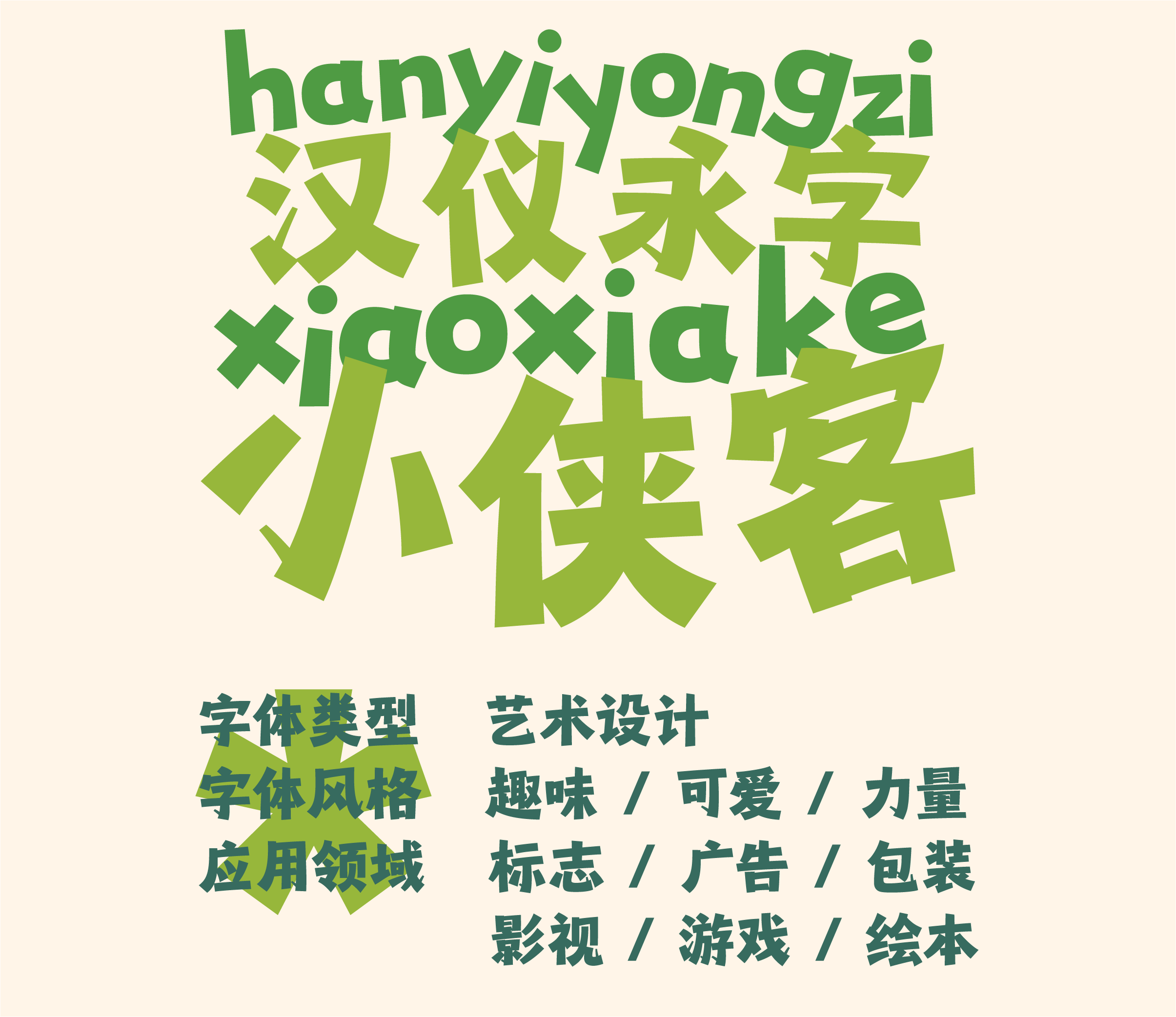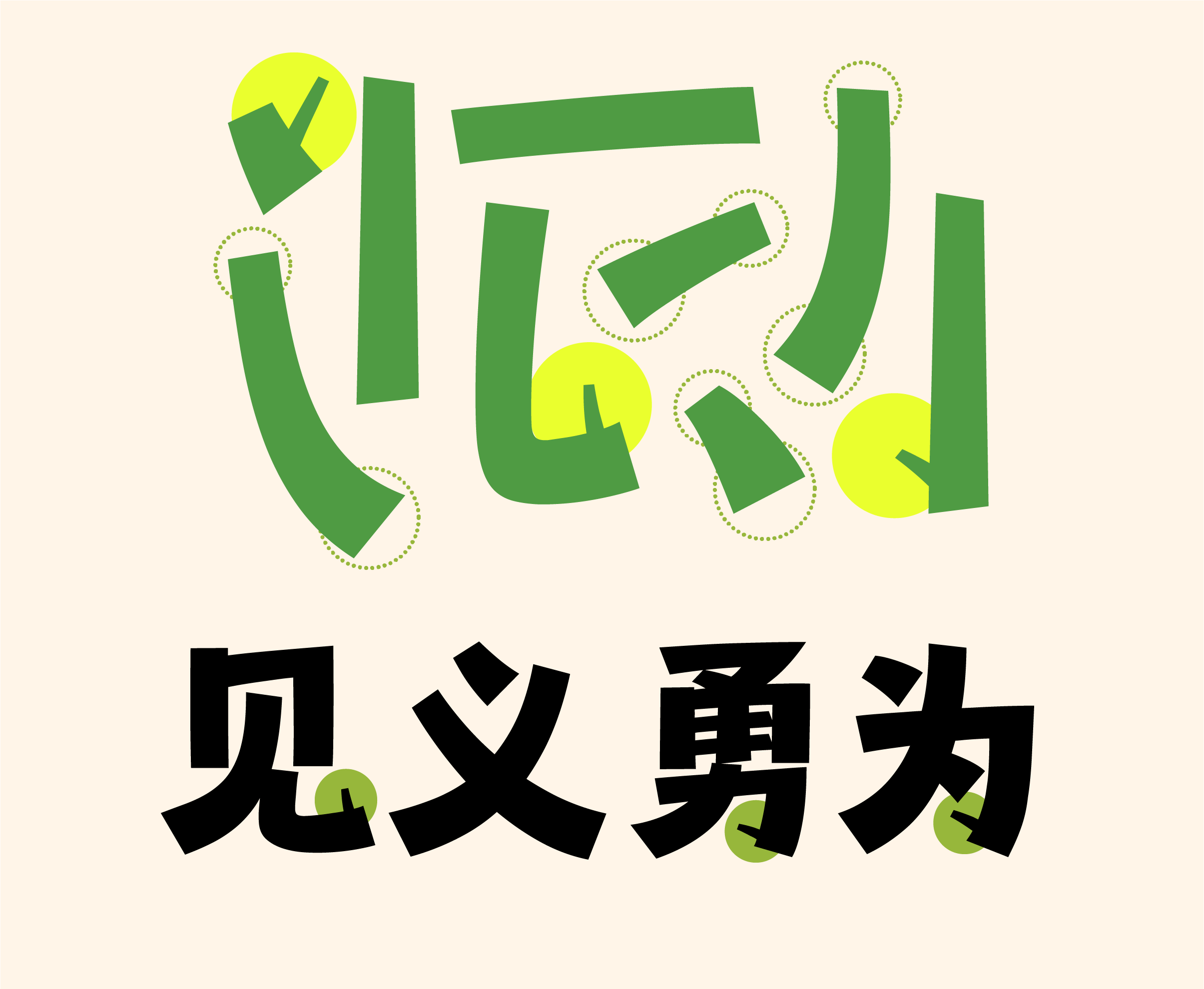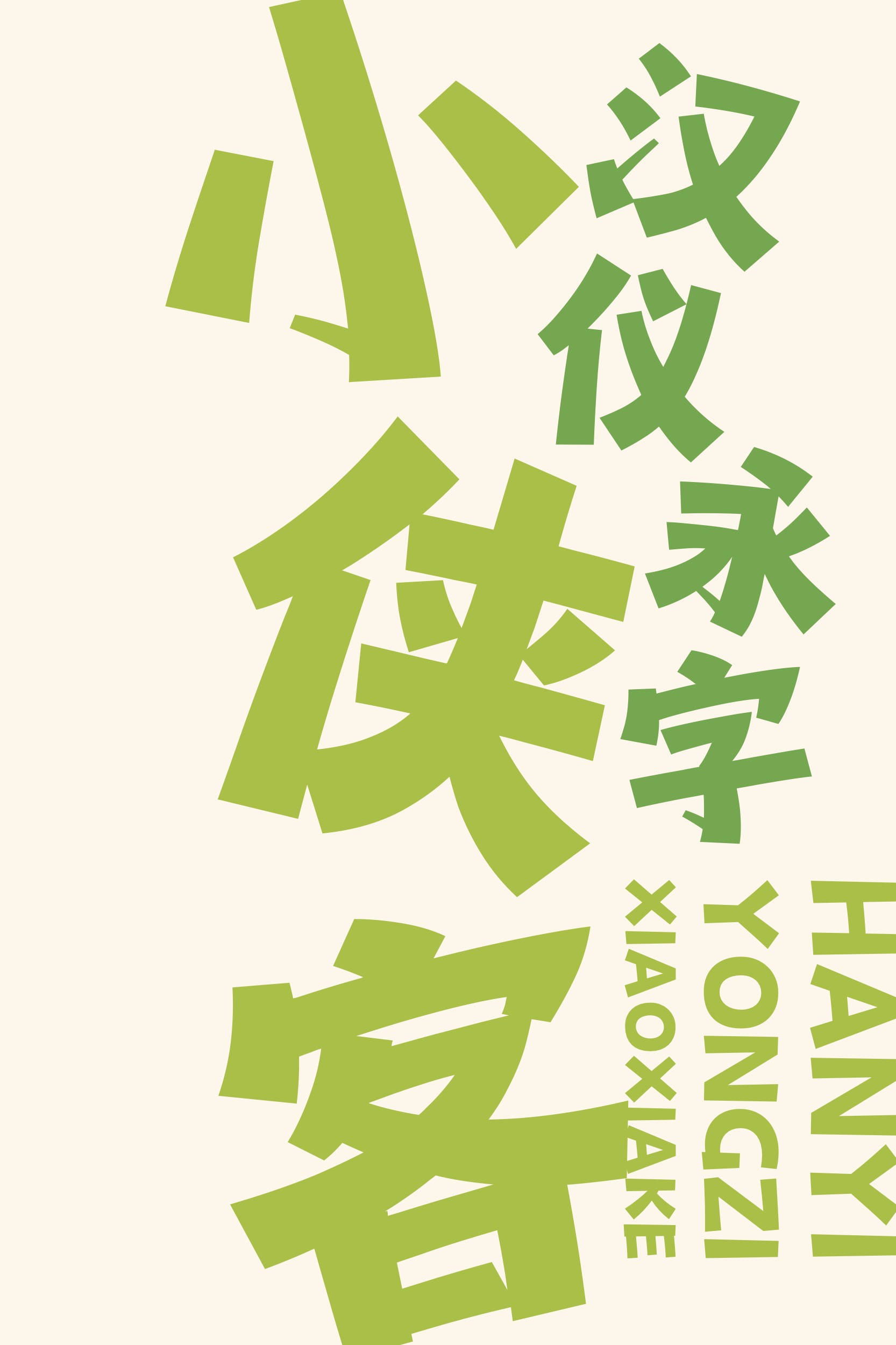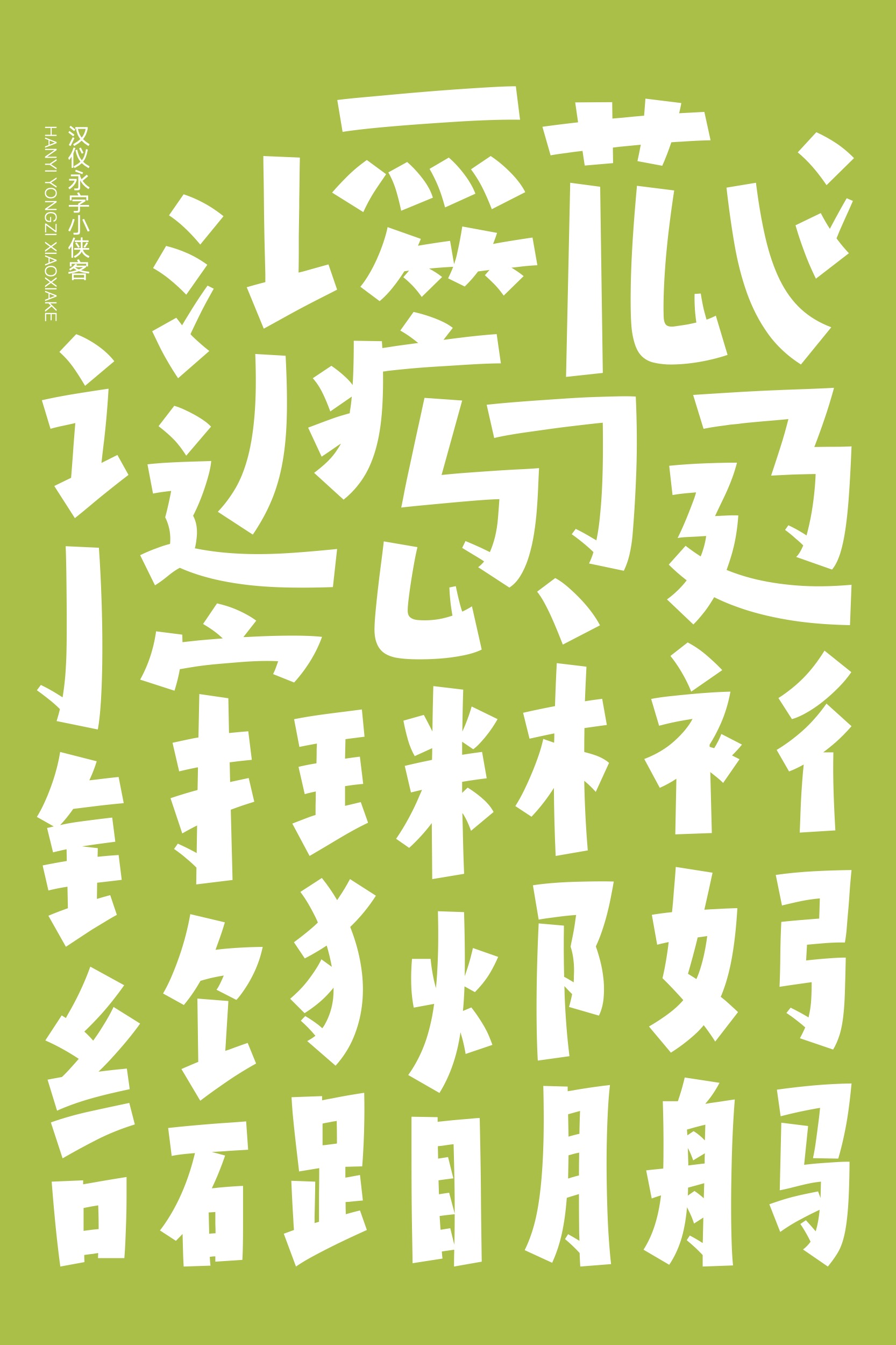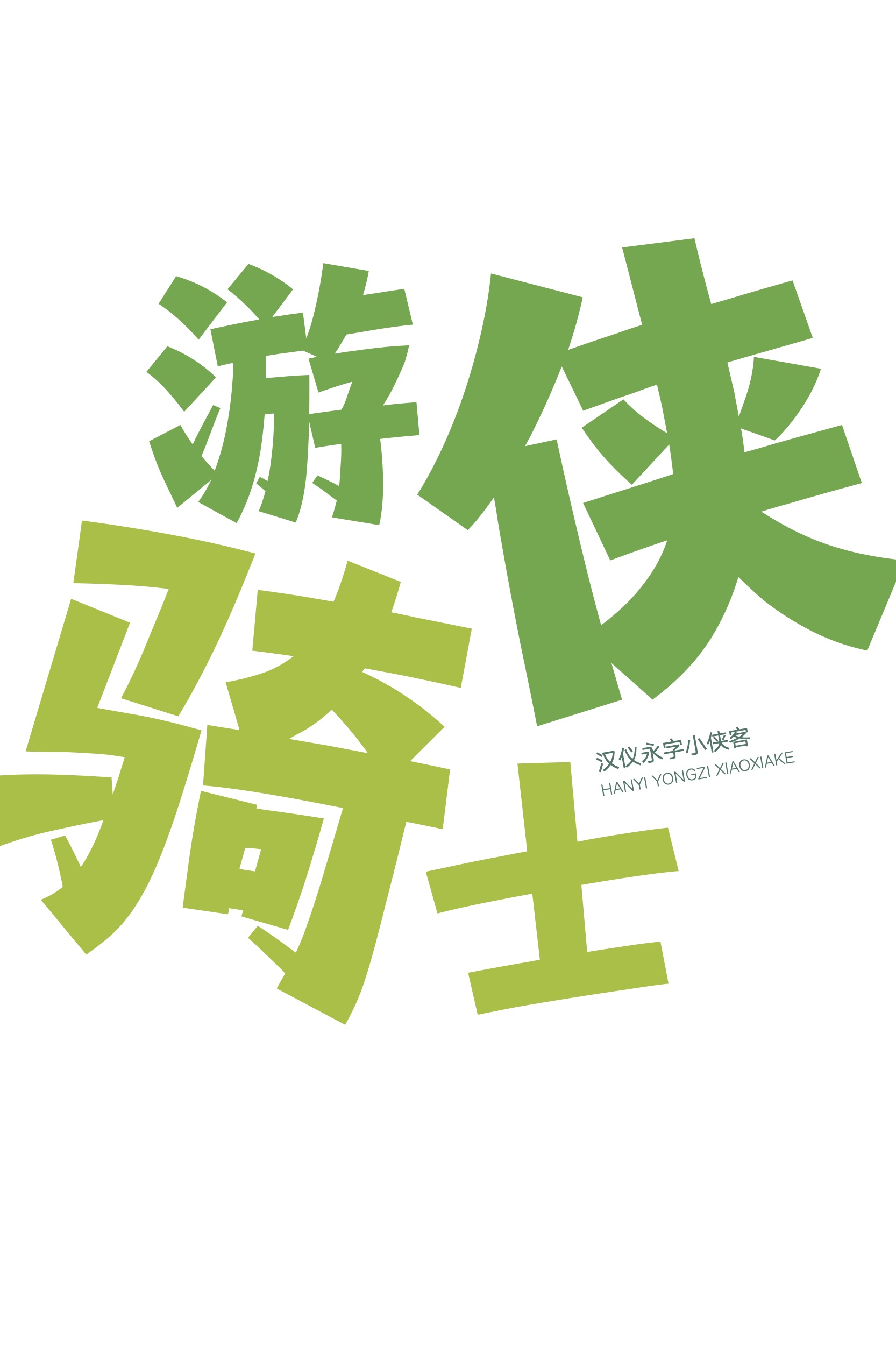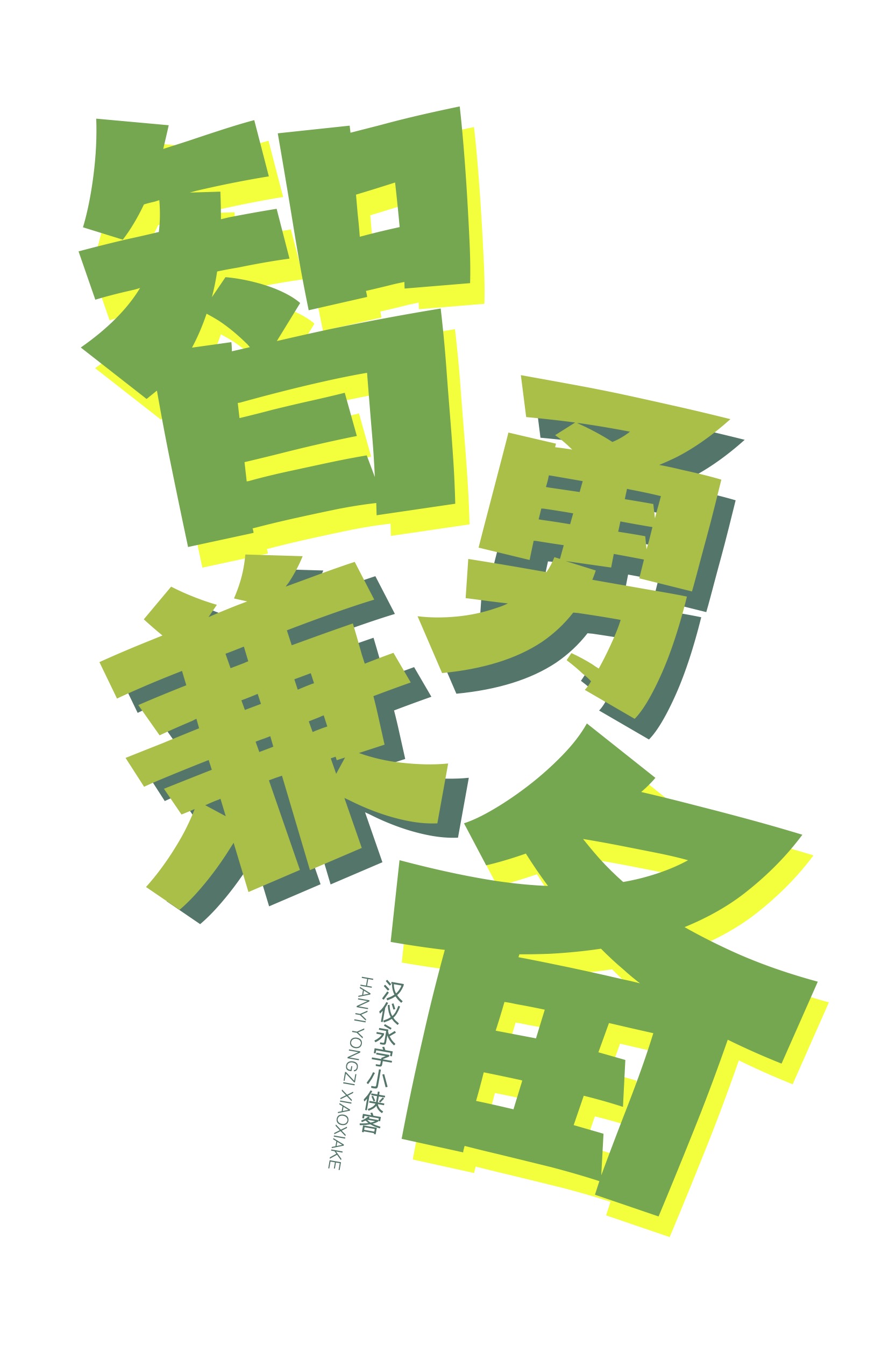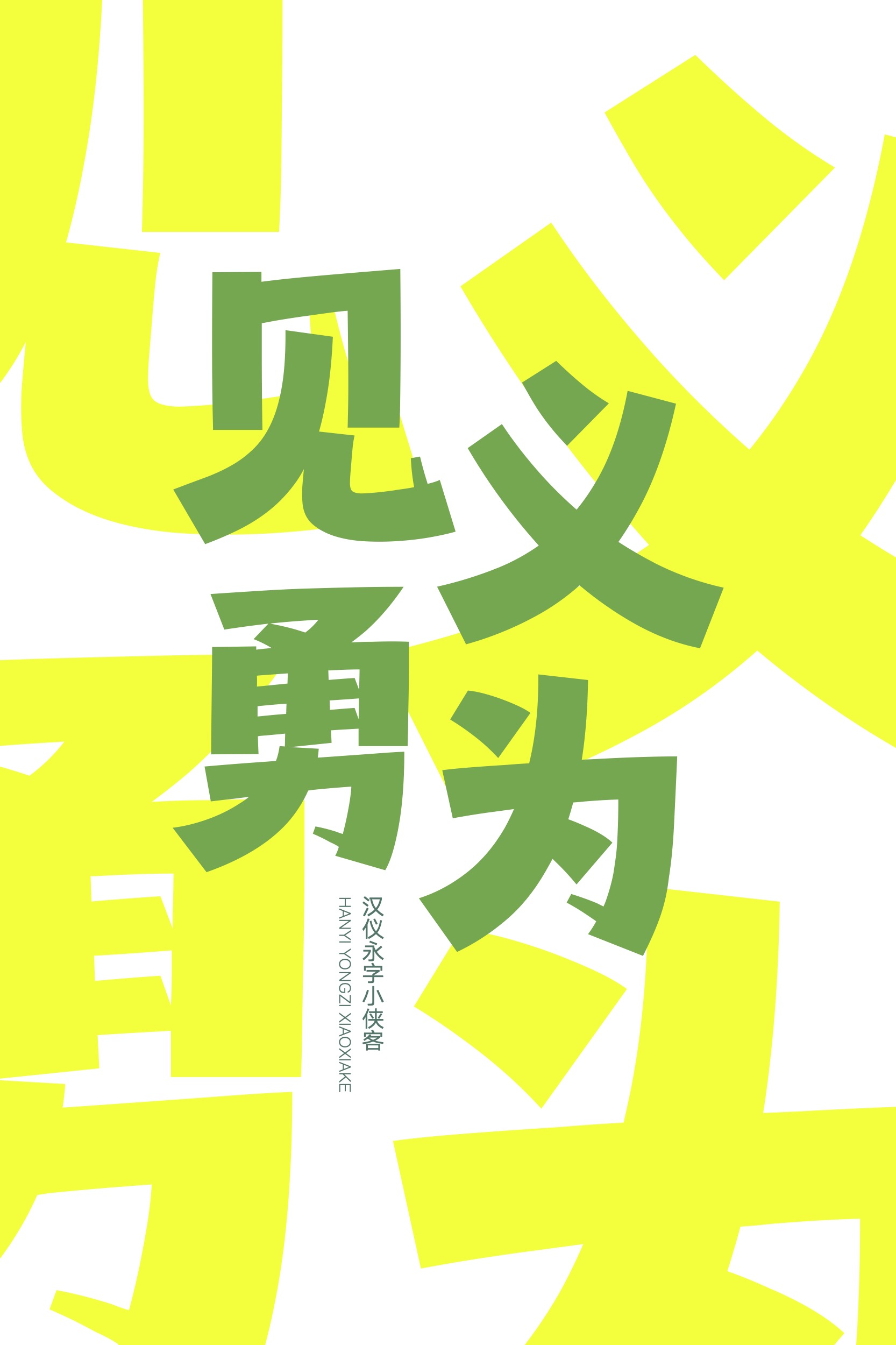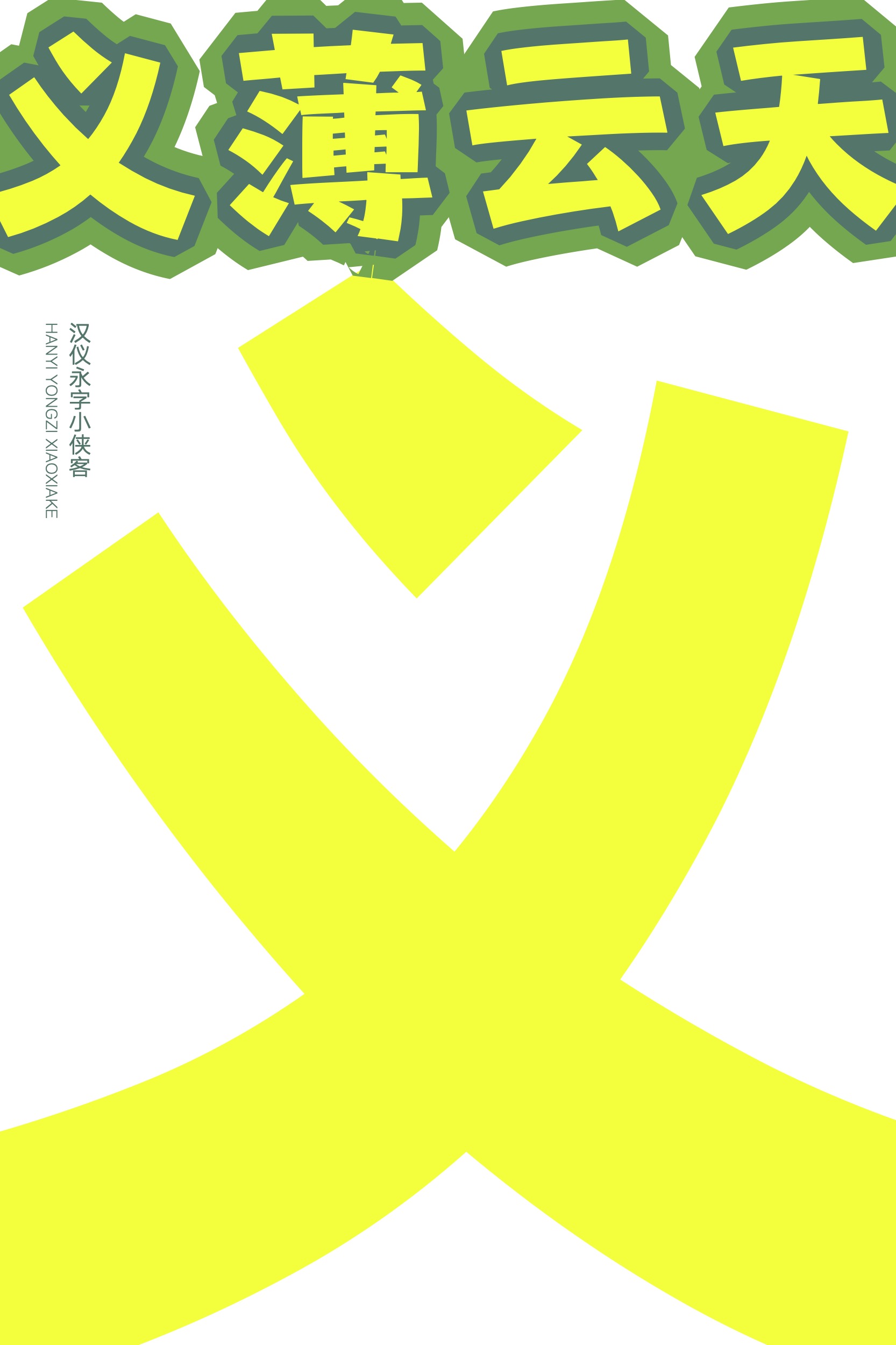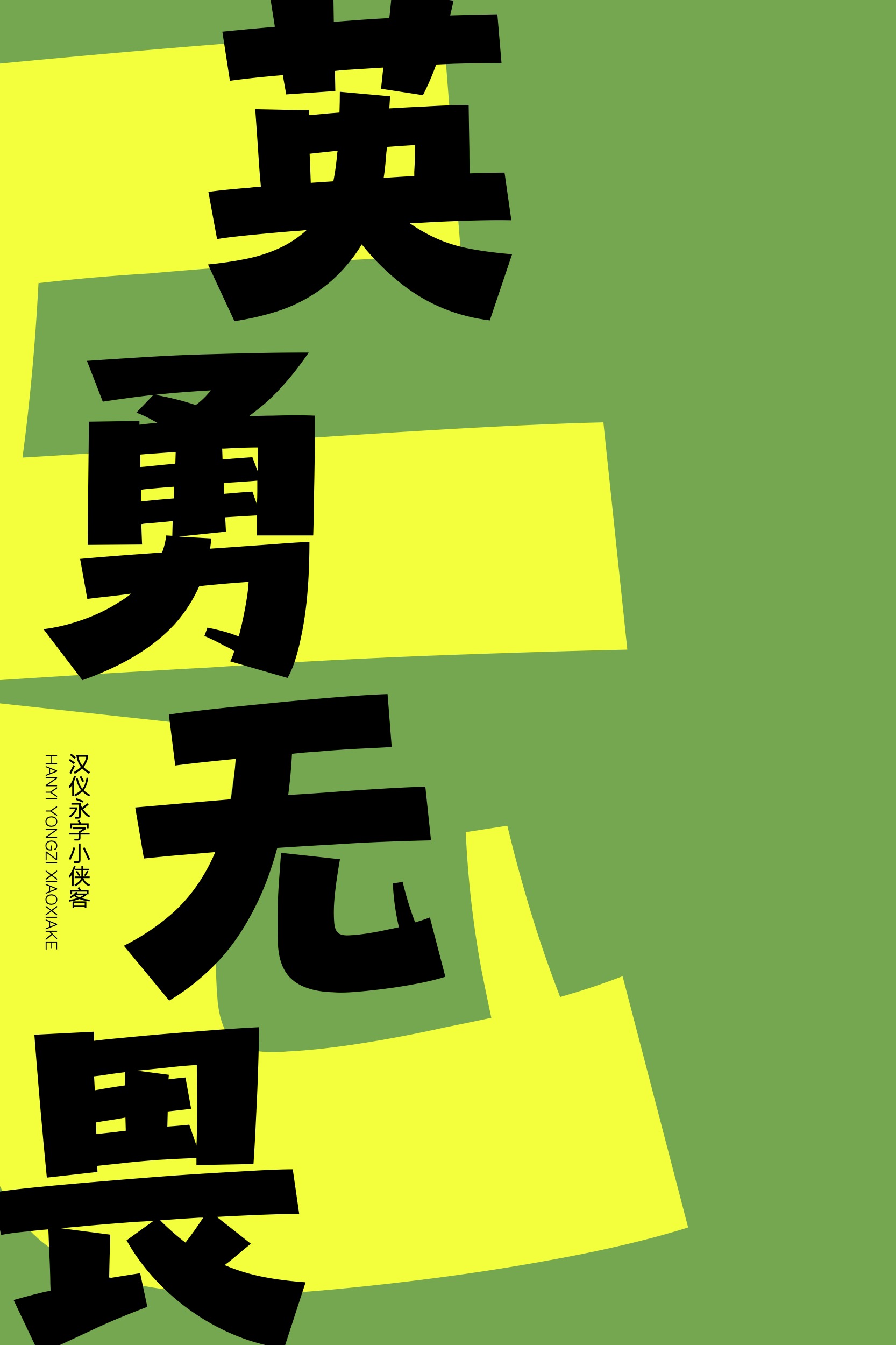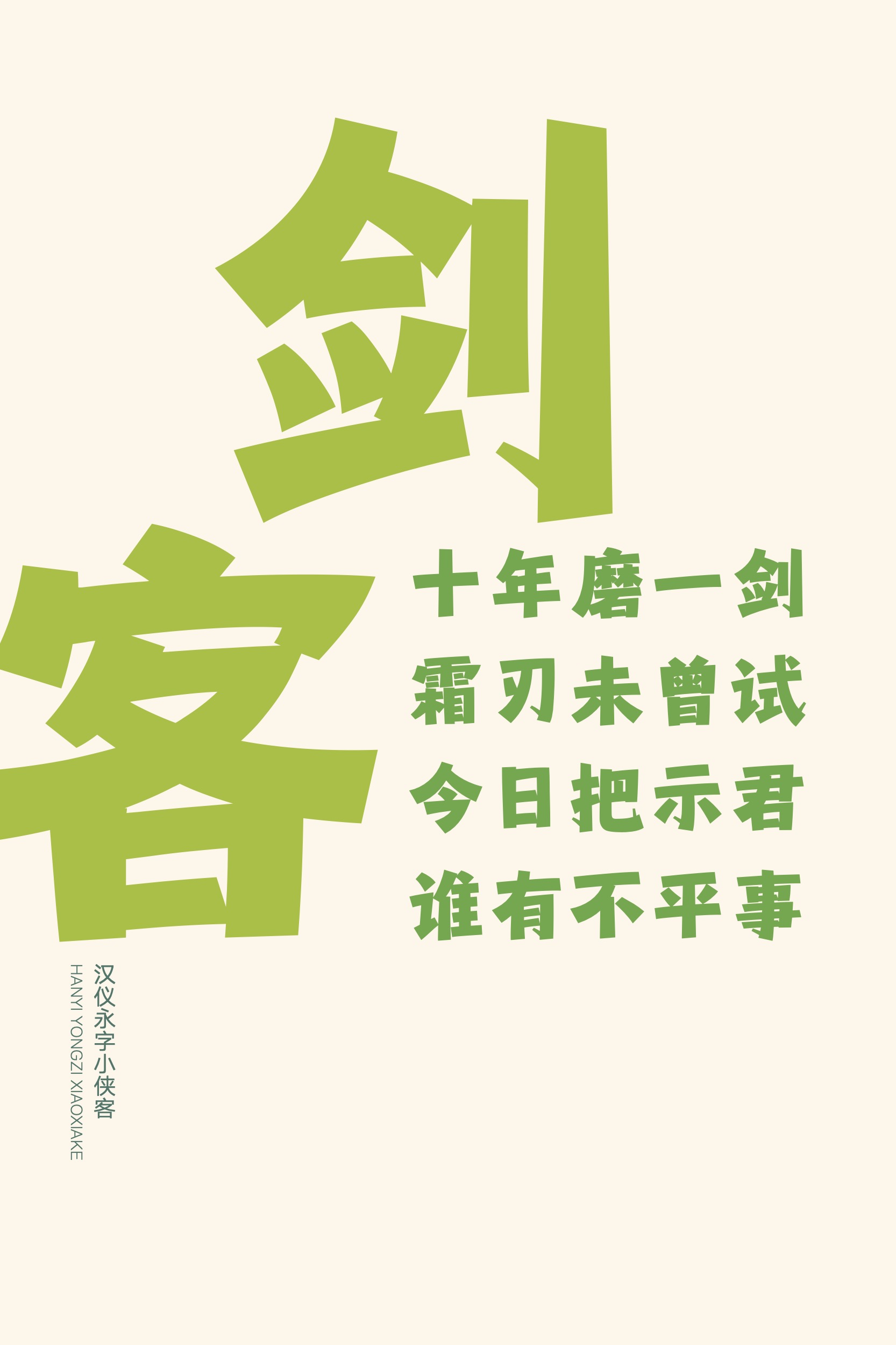
汉仪永字小侠客
汉仪永字小侠客是由永字社创作的一款饱满又有灵动细节的装饰字体。向右上倾斜的动势、带有粗细变化的笔画、舒展的笔画排布、与主笔有着粗细差异的细小钩画,这些特征构成了干脆利落、活泼有力的小侠客。这款字体适合作为标题字体应用于产品包装、影视游戏、书籍绘本等使用场景,增添活力与趣味。
字形饱满有力。
横向笔画向右上倾斜带出整体的动势。
笔画略有粗细变化,排布舒展,细小的钩画轻巧挑出,与主笔形成强烈的粗细对比。
西文部分干脆利落,有粗细变化,如同小侠客一般充满活力。